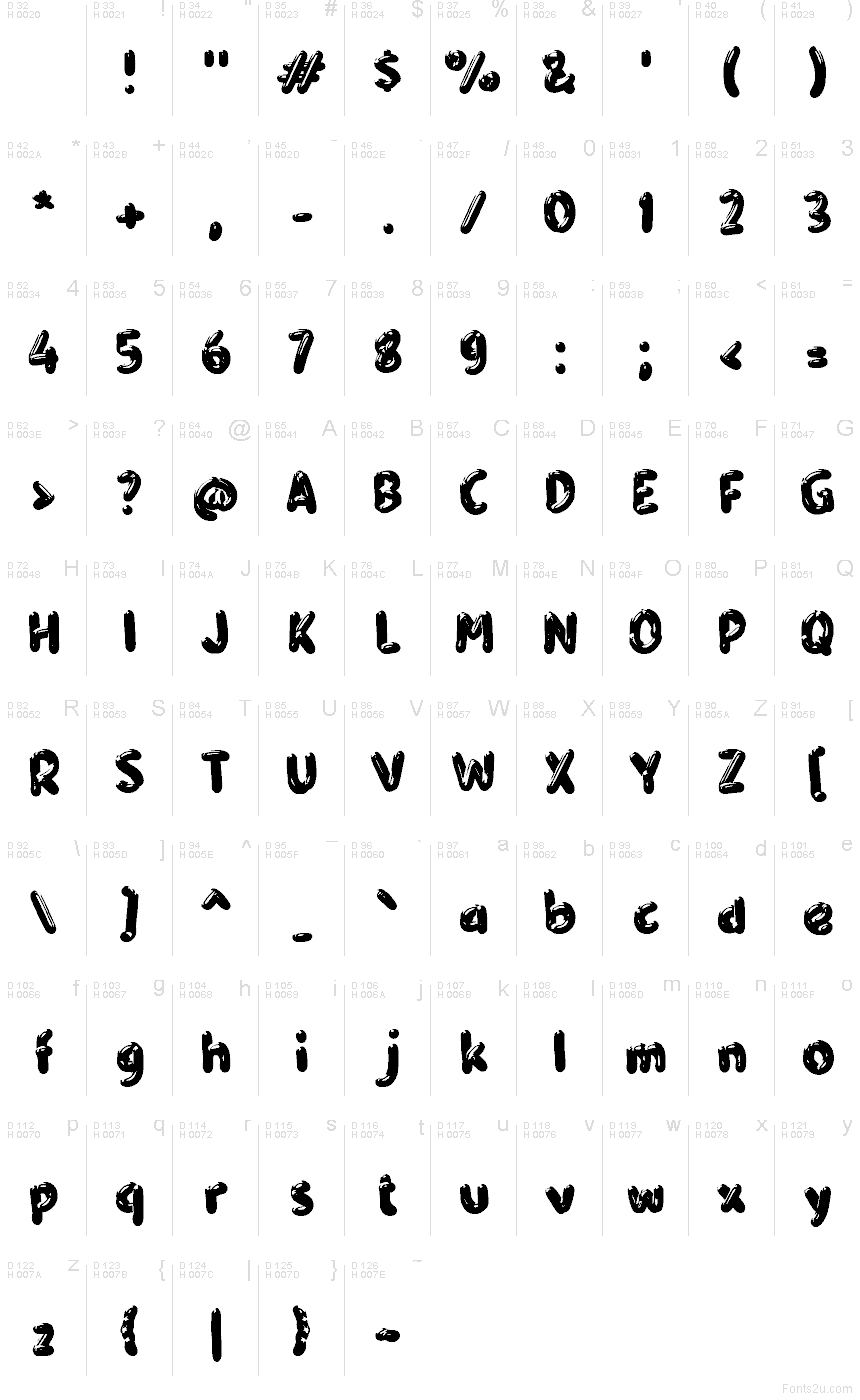
Yableton
Yableton, da Wep, é uma fonte cartoon de exibição gratuita, formada por silhuetas pretas infladas com recortes brancos brilhantes e pequenas entalhes nas bordas superiores. Esse tratamento visual repetitivo e reluzente confere às letras uma presença de história em quadrinhos, lembrando mais a estética de mascotes pintadas à mão do que um estilo de fonte comum.
Funciona perfeitamente em capas de livros infantis, embalagens de doces, convites de festas, miniaturas de YouTube e letreiros comerciais onde suas formas arredondadas e volumosas podem exercer um papel gráfico de destaque. Os reflexos de luz e as bordas marcadas ajudam a compor logotipos curtos ou títulos no estilo sticker, que exigem uma silhueta animada e saltitante em vez de letras convencionais.